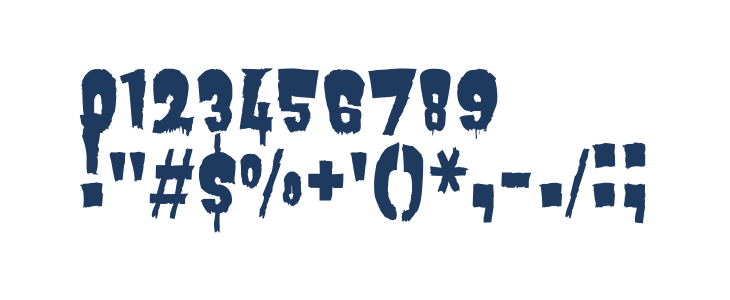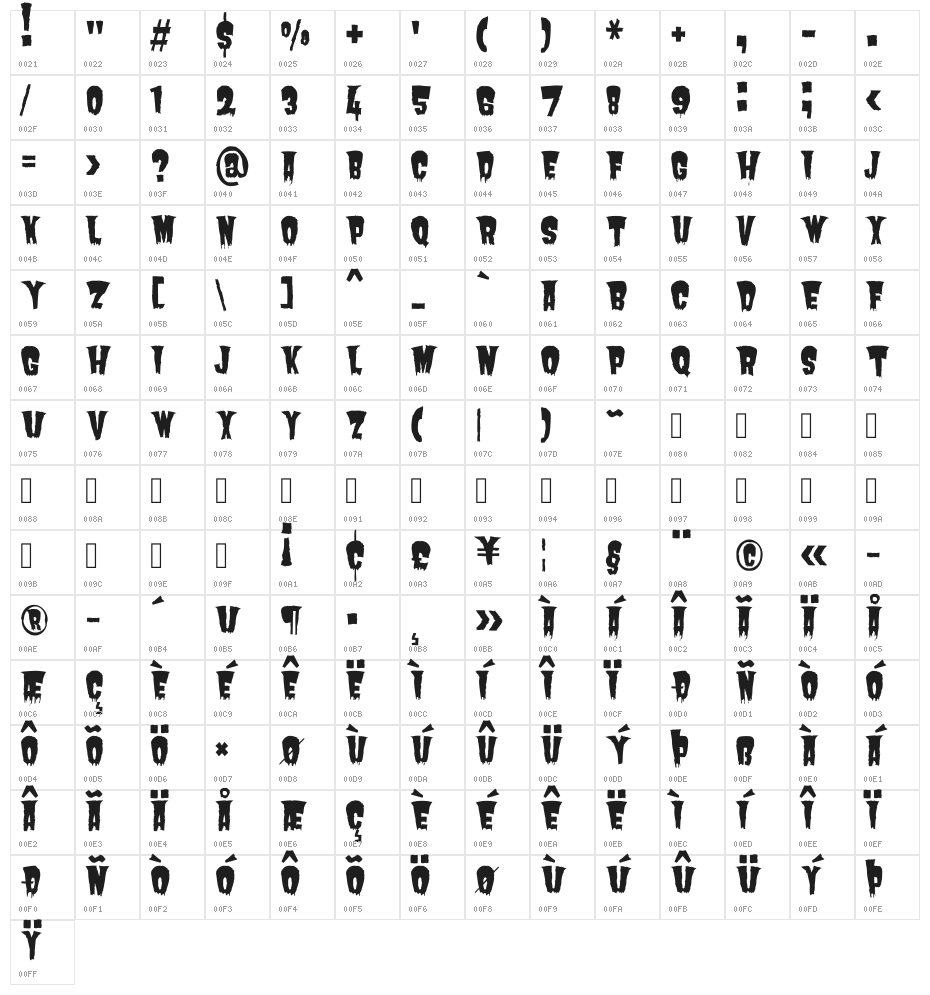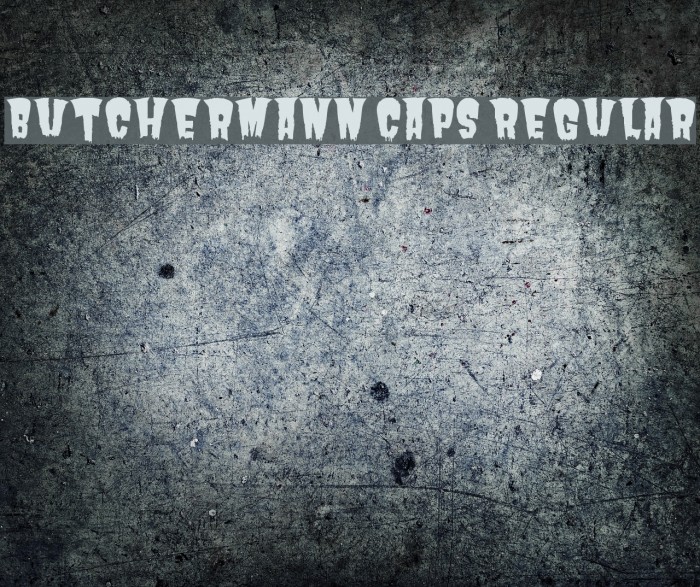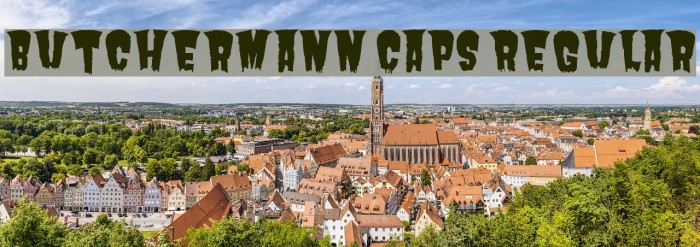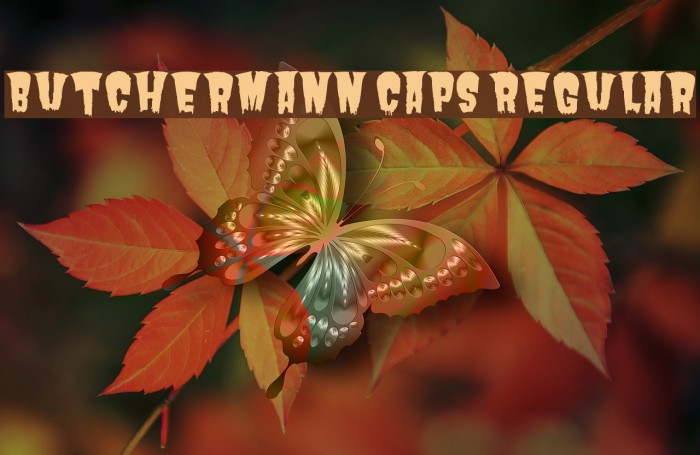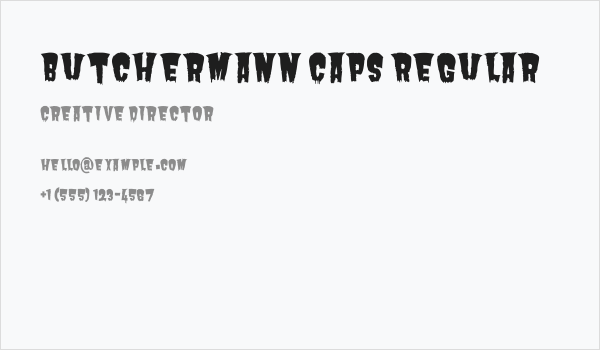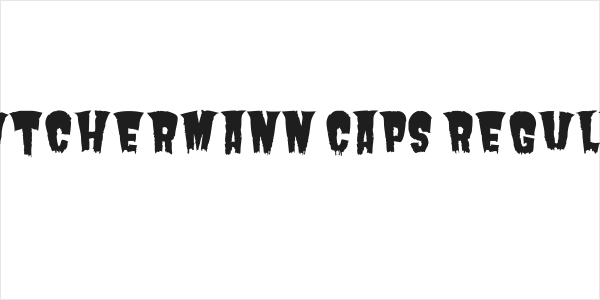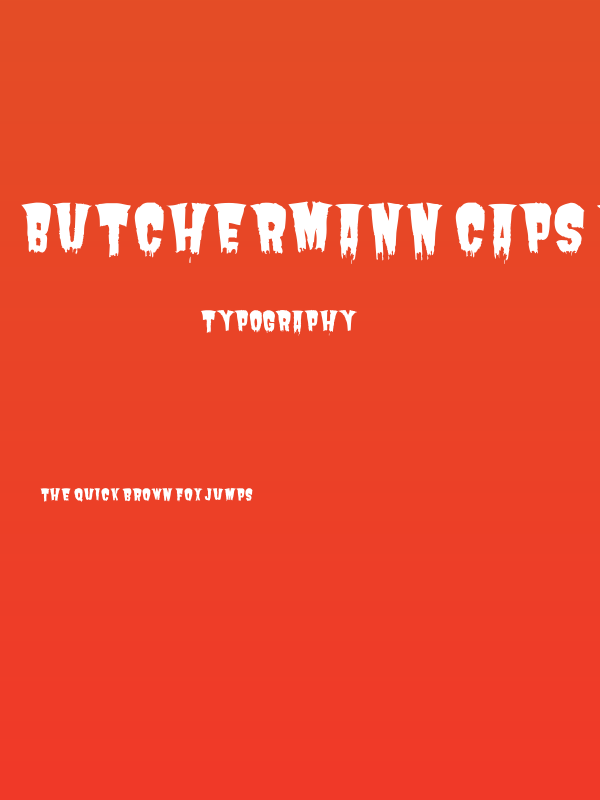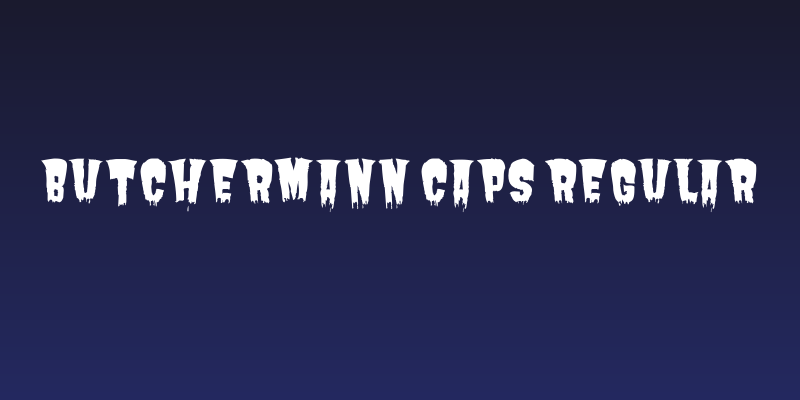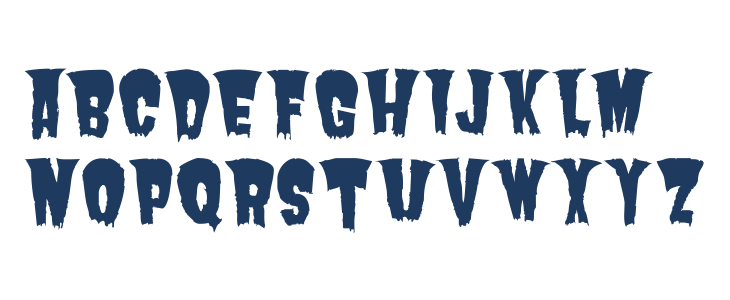
Butchermann Caps Regular Font
| Vorgeschlagene Projekte | Ideal for Halloween posters, horror movie titles, themed event invitations, and spooky merchandise designs. |